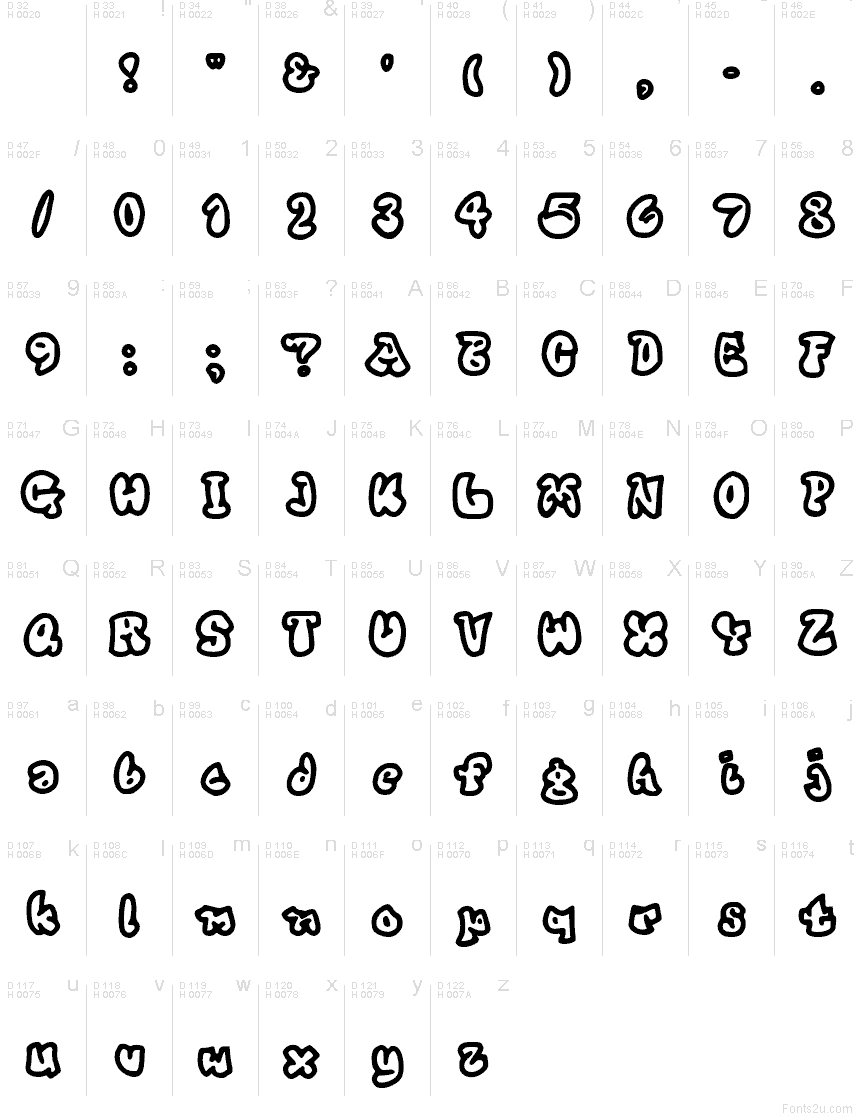
Darrell je bezplatné komiksové displejové písmo s plnými, nepravidelnými písmeny a volnou ručně kreslenou obrysovou linkou. Zaoblené tvary se nepředvídatelně roztahují a zužují, podobně jako gumové komiksové nápisy. Nepravidelné tvary nepůsobí uhlazeně, ale živě.
Tento kreslený styl se skvěle hodí pro dětskou zábavu, komediální plakáty a hravou herní grafiku. Obalům na svačiny nebo netradičnímu merchandise může dodat vzhled ručně kresleného písma. Darrell nejlépe vynikne v projektech, které si žádají velké, humorné nápisy schopné splynout s uměleckým dílem.
Darrell